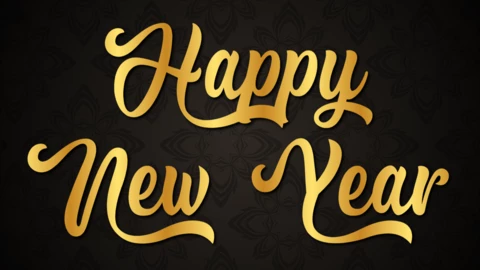
Роскошный золотой шрифт поздравления с Новым годом
Hindi Stylish Font Эффект текста
Создание текстового эффекта "Hindi Stylish Font" Роскошный золотой шрифт поздравления Новым годом с помощью нашего онлайн-генератора пользовательских шрифтов.